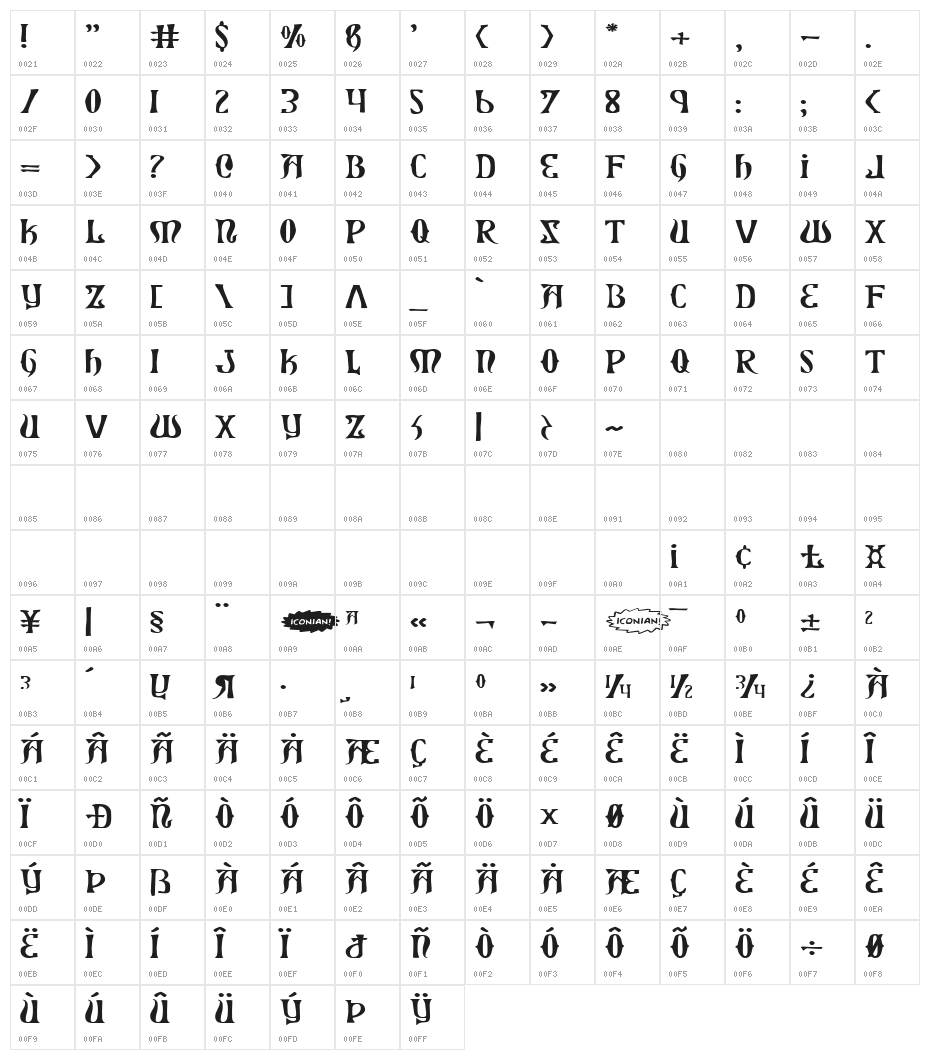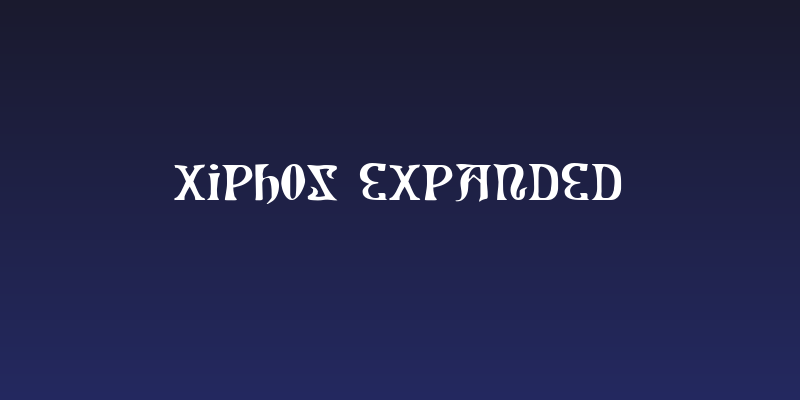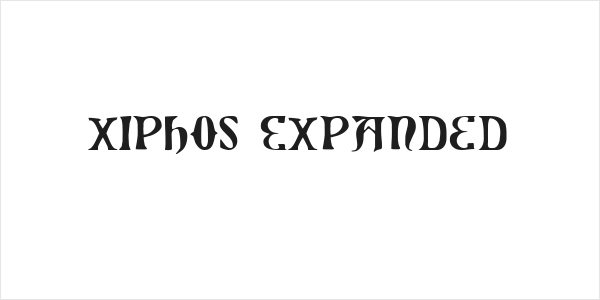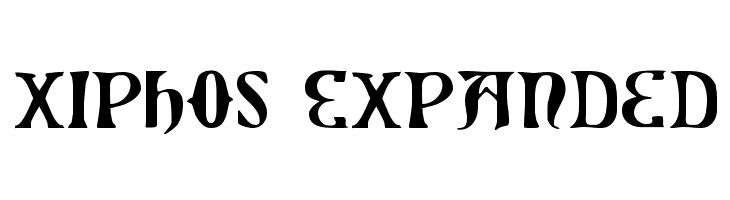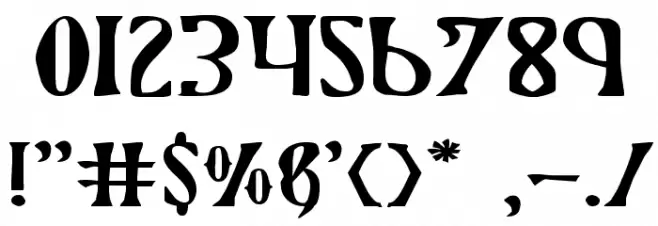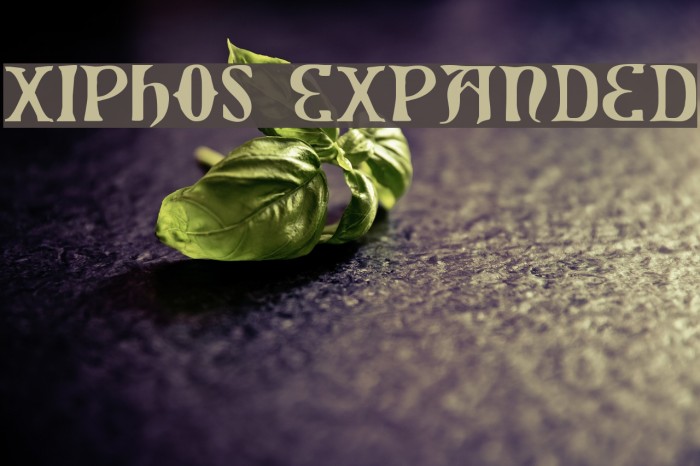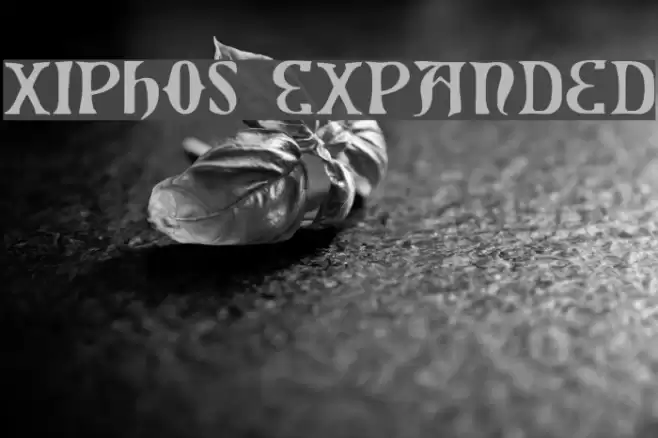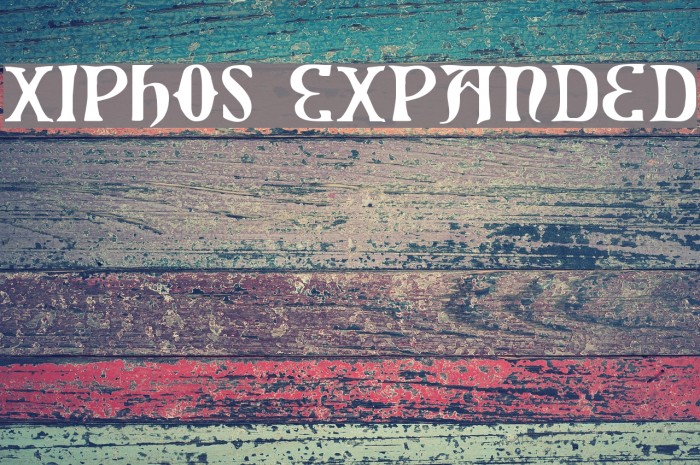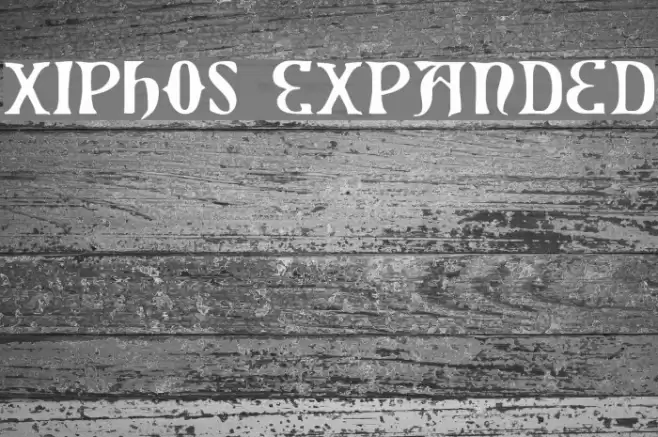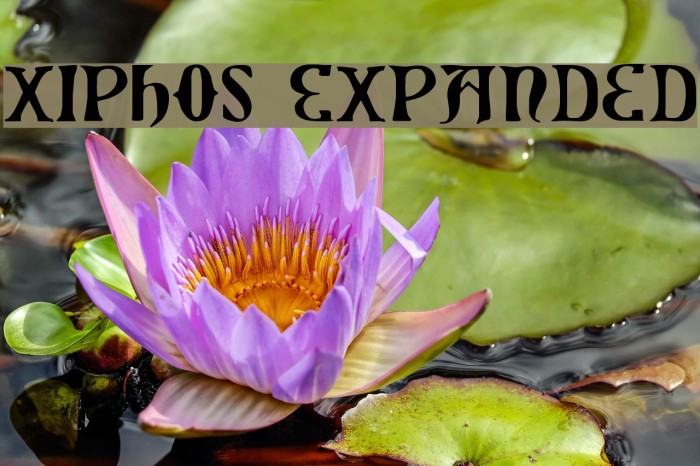
Xiphos Expanded Font
| Vorgeschlagene Projekte | Ideal for fantasy book covers, medieval-themed events, video game titles, and branding that requires a historical or gothic touch. |